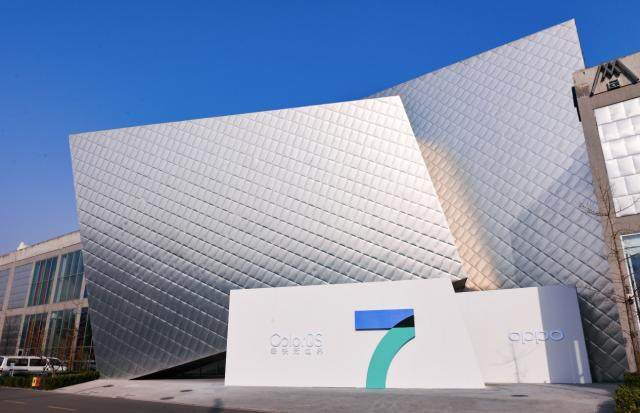
环球网科技综合报道】11月20日,OPPO正式发布全新系统ColorOS 7。发布会期间,OPPO宣布OPPO Sans字体免费授权全社会使用,包括商用。
OPPO Sans字体于2019年4月份正式发布,中文部分由汉仪字库字体设计总监朱志伟指导,黄珍元设计完成,西文部分则由美国 Pentagram 五角公司设计,汉仪字库西文项目组负责人张暄协作完成。该字体包含226003个字符,采用全新骨架,奉行简洁真实,针对移动端进行像素级优化。根据OPPO官方介绍,OPPO Sans字体定位为全球化品牌字体,共覆盖21个国家语言、11个语种。此次OPPOSans字体成为继阿里巴巴普惠体后又一款授权全社会免费使用的字体。